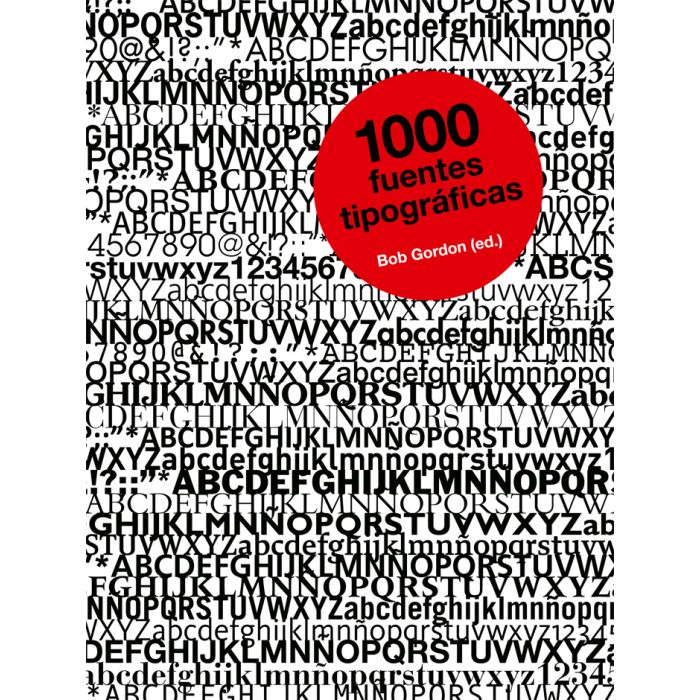
1000 fuentes tipográficas
1000 fuentes tipográficas es un muestrario de mil familias tipográficas completas que han sido recopiladas y seleccionadas por un equipo de experimentados profesionales de la tipografía. Cada fuente está ilustrada a través de la muestra estándar alfanumérica, aplicaciones textuales en distintos ajustes y estilos, caracteres y letras sueltas a gran tamaño y, en numerosos casos, ejemplos de usos en trabajos reales.
A partir de sus características básicas o su posible contexto de aplicación, las mil fuentes se han ordenado en las siguientes secciones: con remates, de palo seco, para rotulación, Script, para carteles y publicidad, monoespaciadas, para web y pantalla, huecas y estarcidas, ornamentales, de símbolos y dingbats, de fantasía, e ilustrativas. Sobre cada muestra se incluyen también detalles descriptivos e históricos relevantes para determinar su uso y sus connotaciones.
Además del índice alfabético para localizar las fuentes, al final del libro se incluye la biografía de algunos de los diseñadores -clásicos y contemporáneos- más importantes en el ámbito de la tipografía, un glosario técnico completo, y una lista de referencias que incluye bibliografía, sitios web y fundiciones digitales.
1000 fuentes tipográficas es, en definitiva, un riguroso catálogo de fuentes pensado para una consulta directa y efectiva, y la rápida identificación del tipo adecuado para cada proyecto.